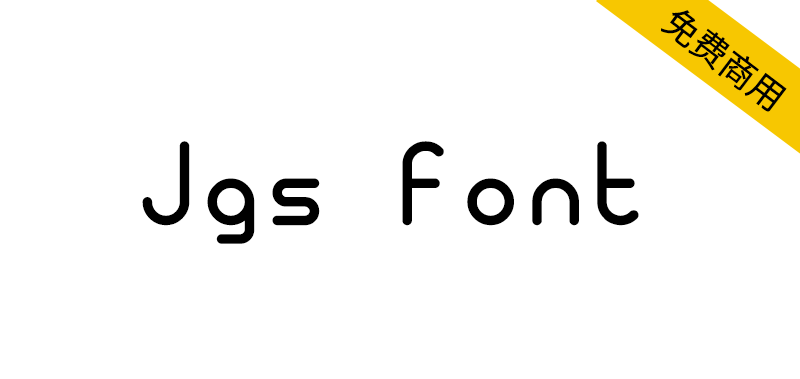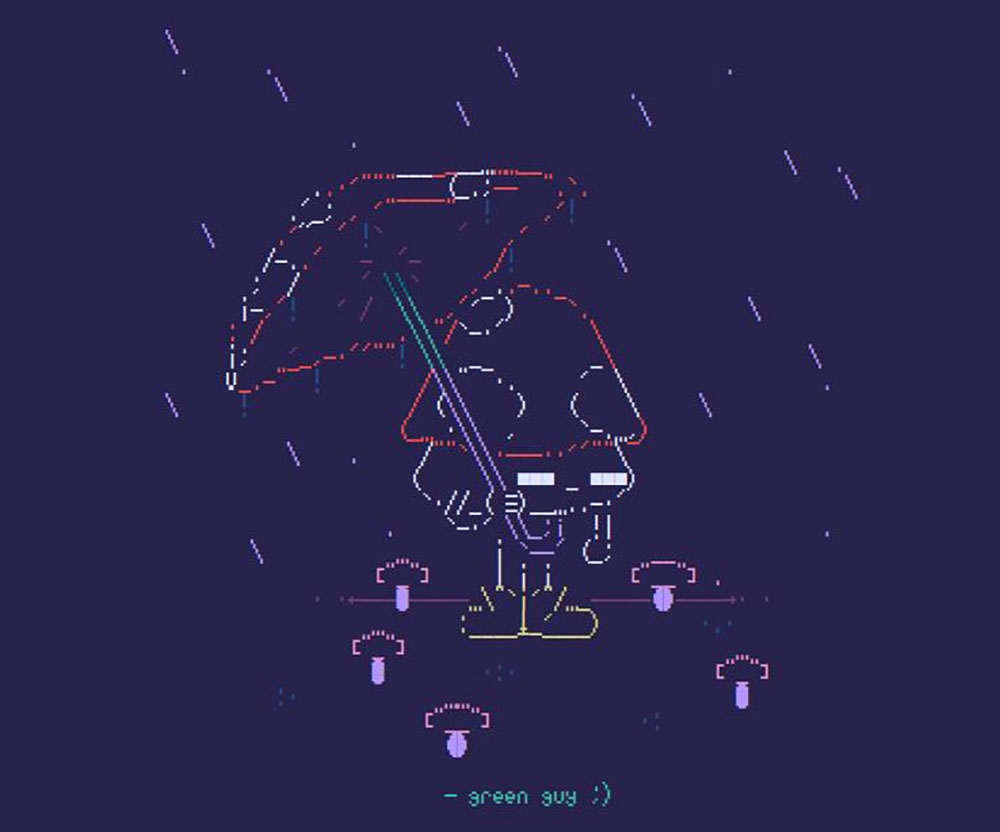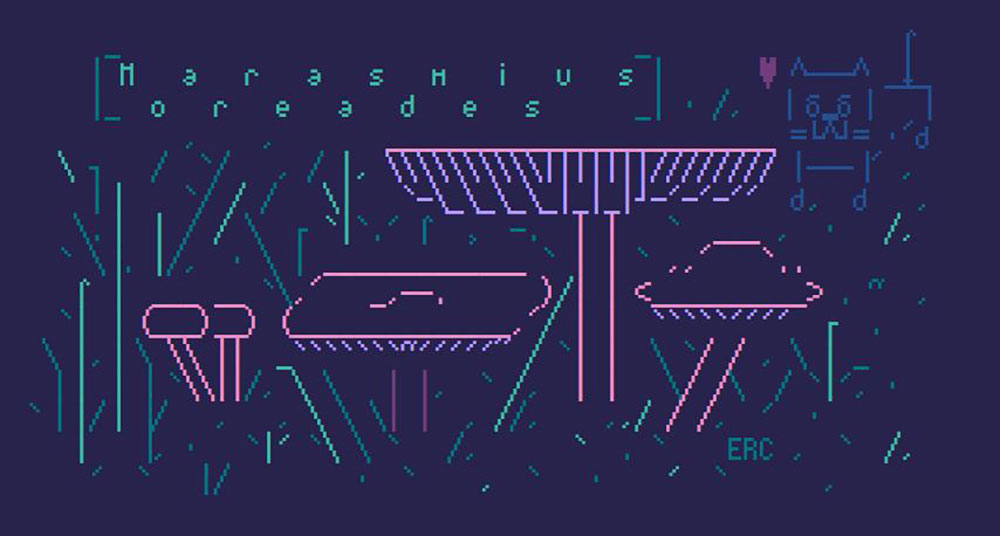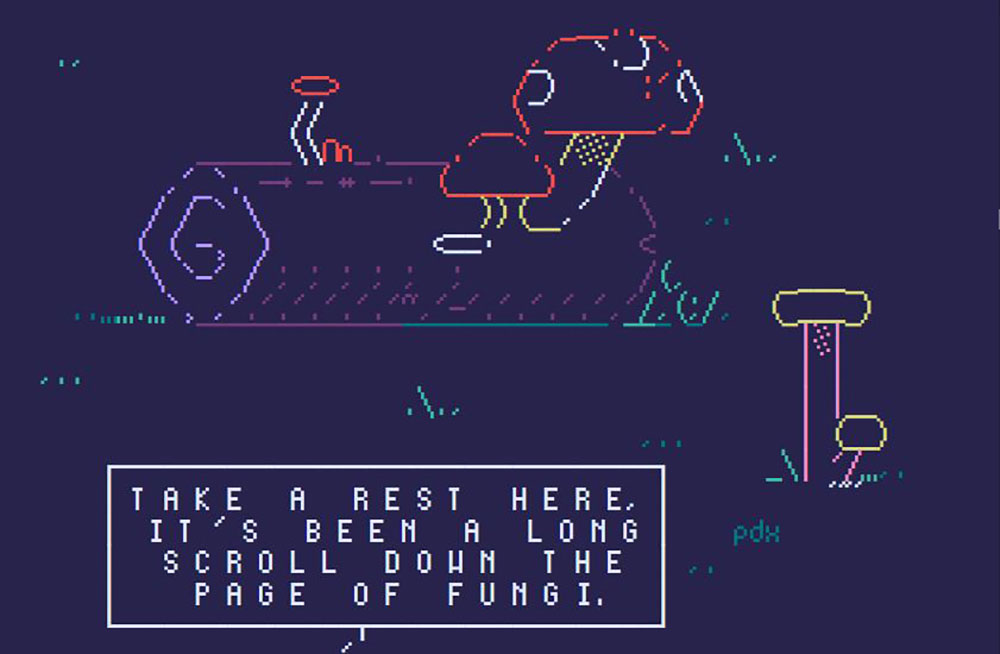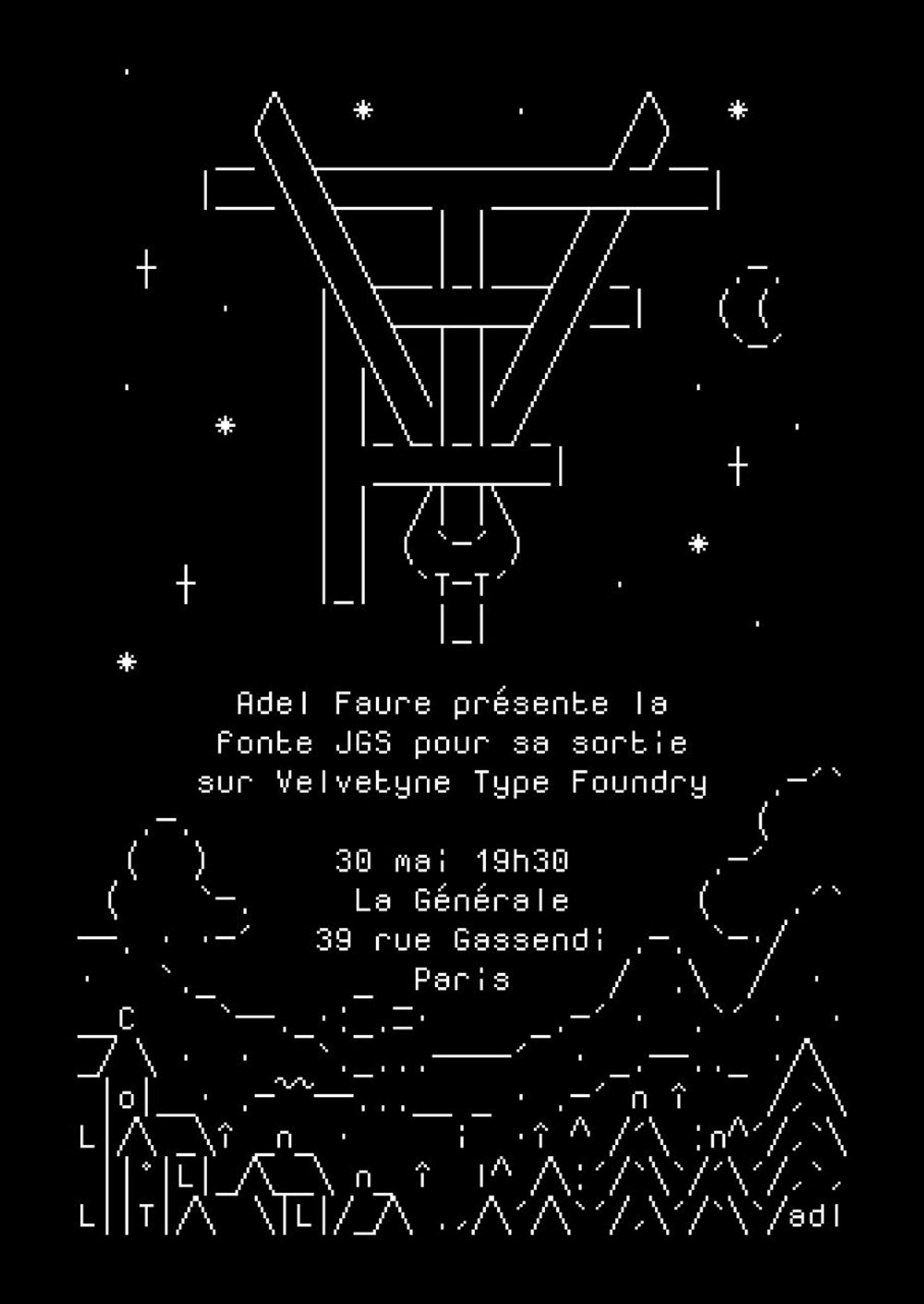
Jgs字体是为了向ASCII艺术的先驱Joan G.Stark(又名Jgs、Spunk)致敬而创建的字体家族。这种字体是专门为绘制ASCII艺术而设计的。它的位图外观和形状突显了文本和绘画之间的模糊性。字符的“图形”属性被夸大了,这取决于ASCII艺术家使用它们的方式。
组成Jgs字体的字形可以从一个字符组合到下一行,也可以从一行组合到另一行。它允许通过字符的关联来产生连续的线条、曲线、框架、图案和灰度级。
为了能够在保持这些像素完美连续性效果的同时改变字体大小,该系列有三种字体可供选择:
Jgs5适用于10倍的正文大小:10px、20px、30px等。
Jgs7适用于14的倍数的正文大小:14px、28px、42px等。
Jgs9适用于18px、36px、54px等倍数的正文大小。
为了获得更好的结果,身体大小和前导需要具有完全相同的值,并对应于上述倍数。
The glyphs that make up Jgs Font can be combined from one character to the next in line or from one line to another. It allows, by association of characters, to produce continuous lines, curves, frames, patterns, levels of gray.
In order to be able to change body size while maintaining these pixel-perfect continuity effects, the family is available in three fonts.
Jgs5 for body text sizes that are a multiple of 10 : 10px, 20px, 30px etc.
Jgs7 for body text sizes that are a multiple of 14 : 14px, 28px, 42px etc.
Jgs9 for body text sizes that are a multiple of 18 : 18px, 36px, 54px etc.
For better results, the body size and the leading need to have exactly the same value and correspond to the multiples cited above.